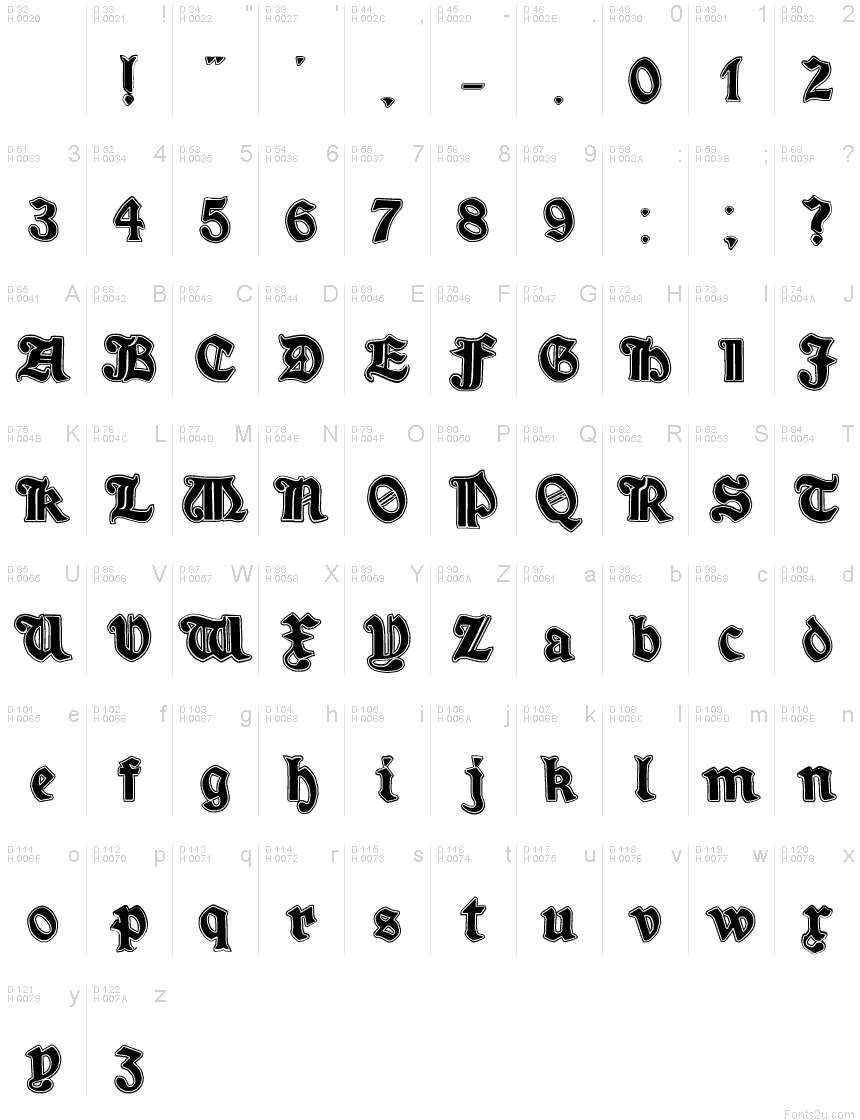
Minim Outline ExtraBold od PJL to darmowy gotycki krój pisma, którego warstwowy kontur zmienia tradycyjne formy blackletter w ostre, emblematyczne sylwetki. Podwójna krawędź i spiczaste zakończenia sprawiają, że litery są wyraziste i heraldyczne, a nie surowe czy odręczne.
Idealnie sprawdzi się na etykietach piw, okładkach książek fantasy, gadżetach muzycznych, plakatach eventowych i grafikach tytułowych gier, gdzie liternictwo pełni funkcję dekoracyjną na równi z informacyjną. Krótkie nagłówki i monogramy zyskują dzięki jasnej linii wewnętrznej, która otwiera gęste gotyckie kształty, nie pozbawiając ich przy tym historycznego charakteru.